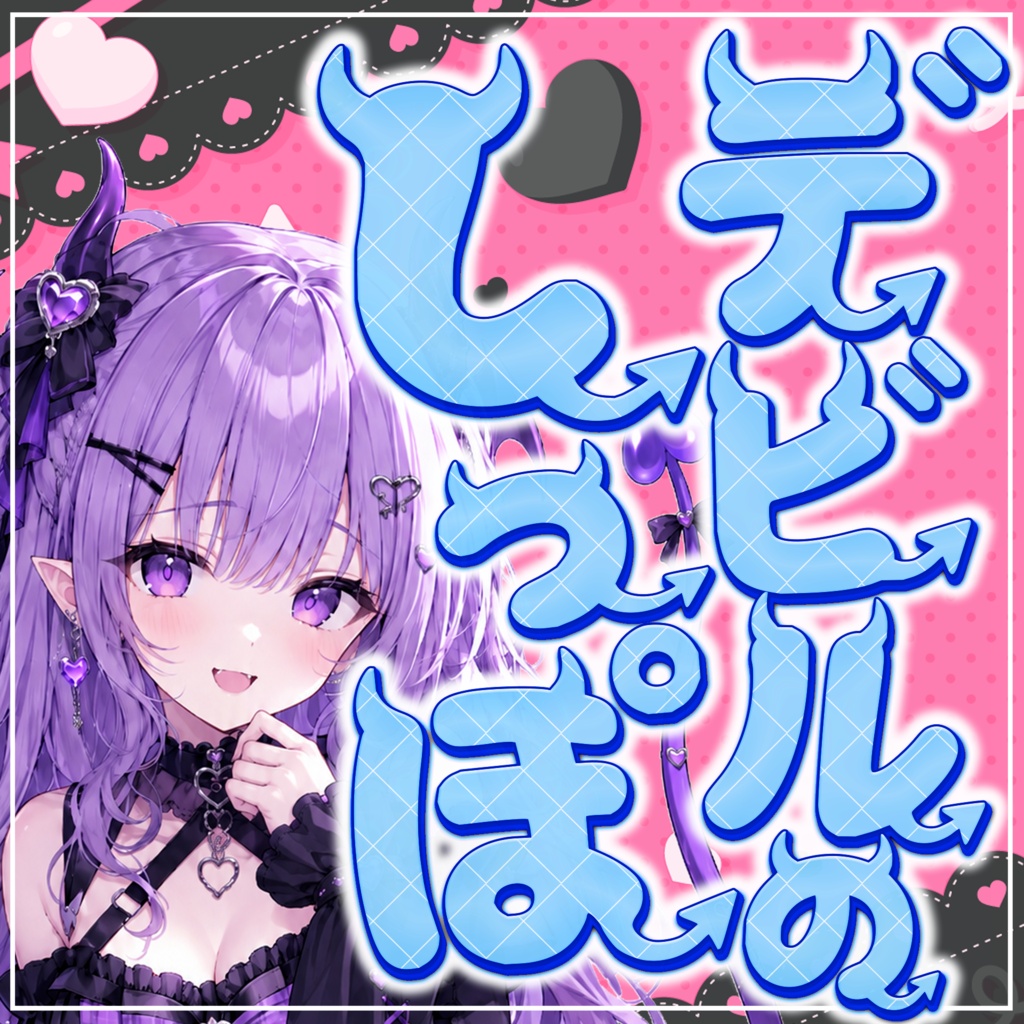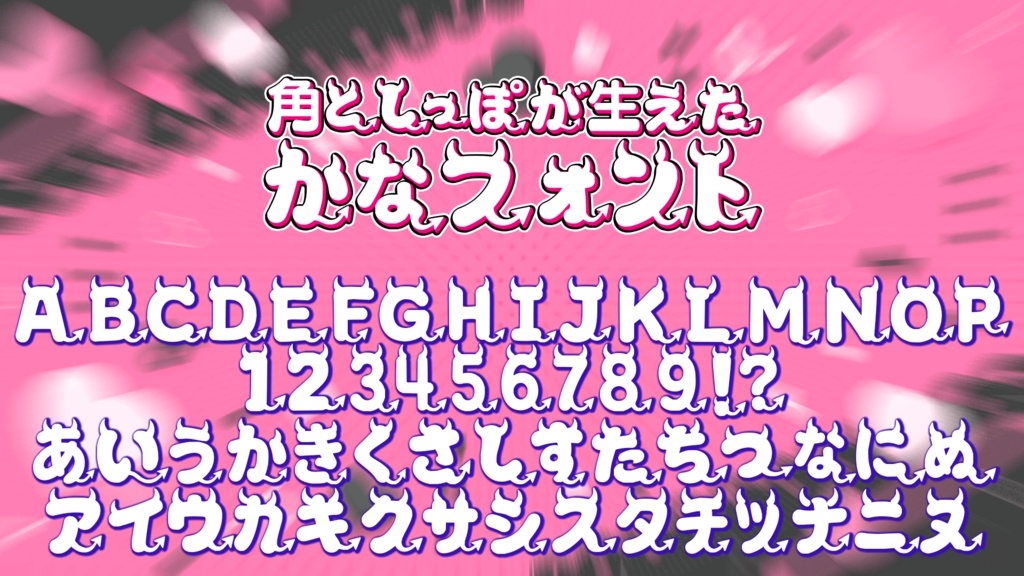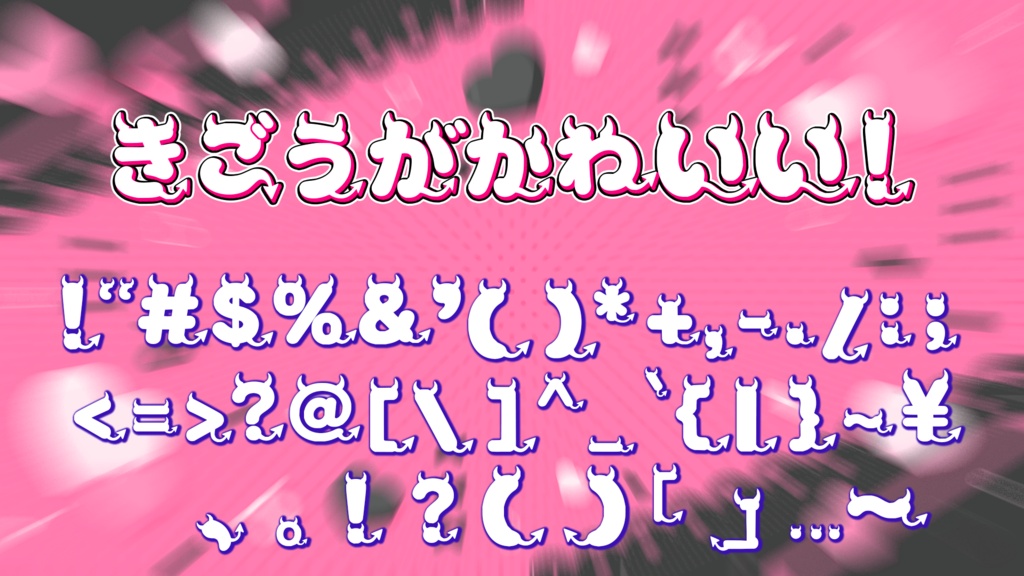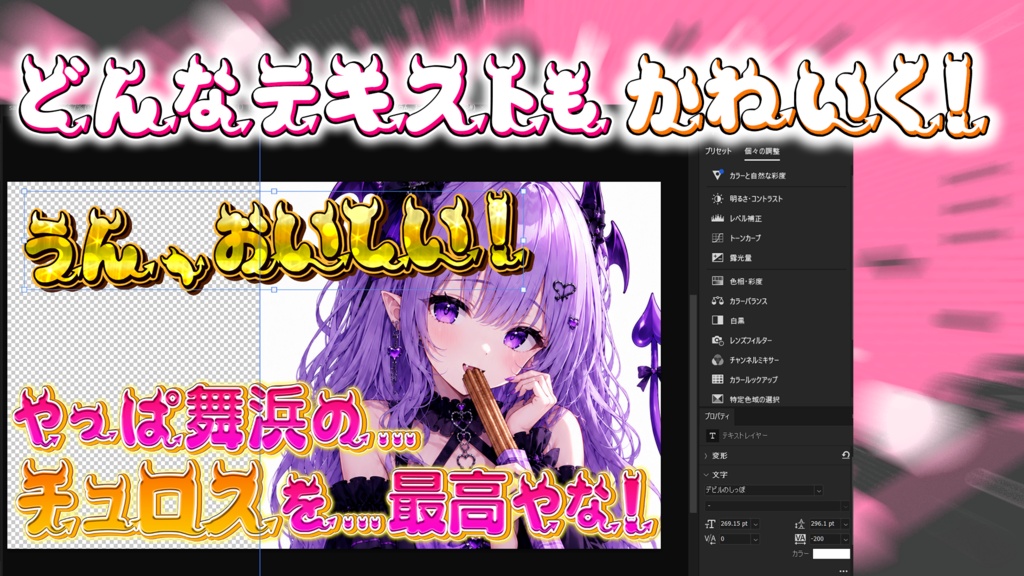
【フリーフォント】角としっぽが生えた悪魔系フォント「デビルのしっぽ」【商用利用OK / VTuber・サムネ向け】
◥◣__________________◢◤ いつもの文字が、ちょっぴり小悪魔に! ◢◤ ̄ ̄ ̄ ̄ ̄ ̄ ̄ ̄ ̄ ̄ ̄ ̄ ̄ ̄ ̄ ̄ ̄ ̄◥◣ VTuberの配信画面や、切り抜き動画のテロップ、YouTubeのサムネイルに使いやすい、太くてポップなデザインフォント 『デビルのしっぽ』を制作しました! ぷっくりとした文字に、悪魔らしい2本の角と、生きているように動くしっぽを組み込んでいます。 単純な文字には少し長めのしっぽを付け、複雑な文字では短いしっぽや角だけにするなど、文字ごとにバランスを調整しました。 元から払いがある文字は、その筆画を自然にしっぽへ変形しています。 日頃の感謝を込めて【完全無料】で配布いたします! 【こんな用途に最適です】 ✅ YouTubeのサムネイルのデカ文字に ✅ VTuberの「歌枠」「雑談」などの配信画面デザインに ✅ 切り抜き動画の「感情的なツッコミ」や「可愛いセリフ」に ✅ ハロウィン・魔界・小悪魔系のタイトルに ✅ ゲーム・同人作品・グッズのロゴデザインに
【重要】収録文字・おすすめの使い方について
本フォントはデザインに特化しているため、 【ひらがな・カタカナ・数字・大文字・小文字アルファベット・一部記号のみ】の収録となります。 漢字は収録されていません。 サムネイル画像では、漢字部分にフォントワークスの「スランプ Std」を使用しています。 漢字が含まれる文章では、漢字部分にスランプなどの太くて個性的な日本語フォントを使用し、ひらがな・カタカナ・英数字部分に『デビルのしっぽ』を使用すると、まとまりのあるデザインに仕上がります。 【収録文字】 ■ ひらがな あぁいぃうぅえぇおぉかがきぎくぐけげこごさざしじすずせぜそぞただちぢつっづてでとどなにぬねのはばぱひびぴふぶぷへべぺほぼぽまみむめもやゃゆゅよょらりるれろわをんゔ ■ カタカナ アァイィウゥエェオォカヵガキギクグケヶゲコゴサザシジスズセゼソゾタダチヂツッヅテデトドナニヌネノハバパヒビピフブプヘベペホボポマミムメモヤャユュヨョラリルレロワンヴ ■ 仮名記号 ・゙゚ー ■ 大文字アルファベット ABCDEFGHIJKLMNOPQRSTUVWXYZ ■ 小文字アルファベット abcdefghijklmnopqrstuvwxyz ■ 数字 0123456789 ■ 半角記号 !"#$%&'()*+,-./:;<=>?@[]^_`{|}~¥ ■ 全角記号 、。!?()「」…〜